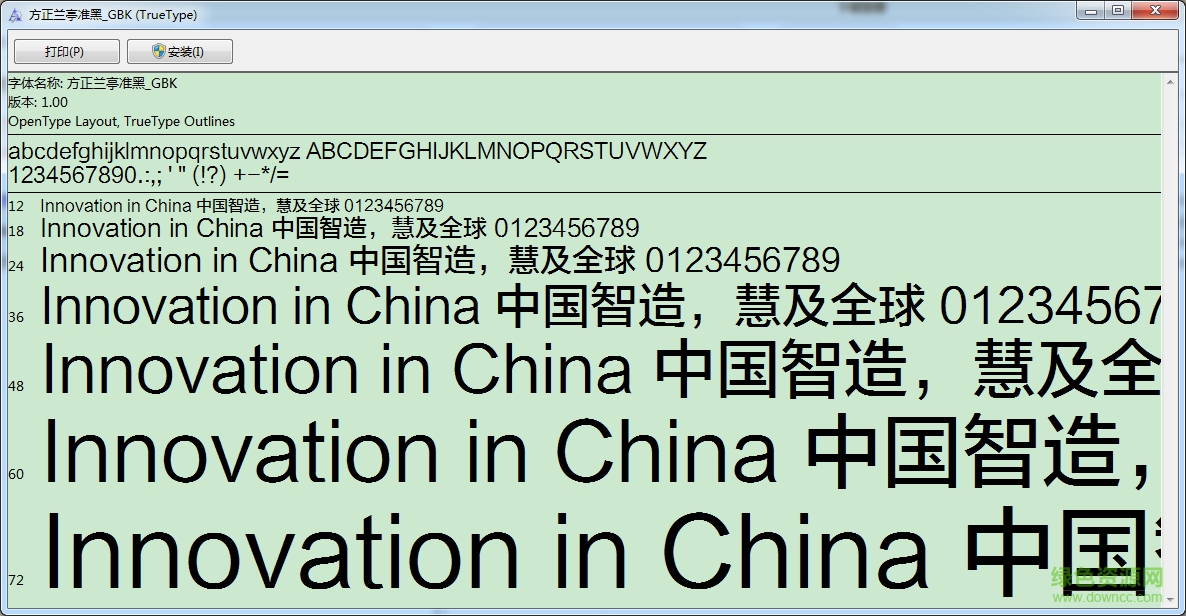
fzltzhunhk gbk1 0
fzltzhunhk gbk1 0是什么字體?fzltzhunhk gbk1 0即為方正蘭亭準(zhǔn)黑字體,字體端正簡(jiǎn)潔鏗鏘有力,使用簡(jiǎn)單涉及多種行業(yè)領(lǐng)域??靵砭G色資源網(wǎng)下載體驗(yàn)吧!
fzltzhunhk gbk1 0字體介紹
fzltzhunhk gbk1 0是一款粗細(xì)適中的中文字體,該字體端正易讀,線條簡(jiǎn)潔。此款字體適用于廣告設(shè)計(jì)、平面設(shè)計(jì)等方面,需要的話可以來下載使用。